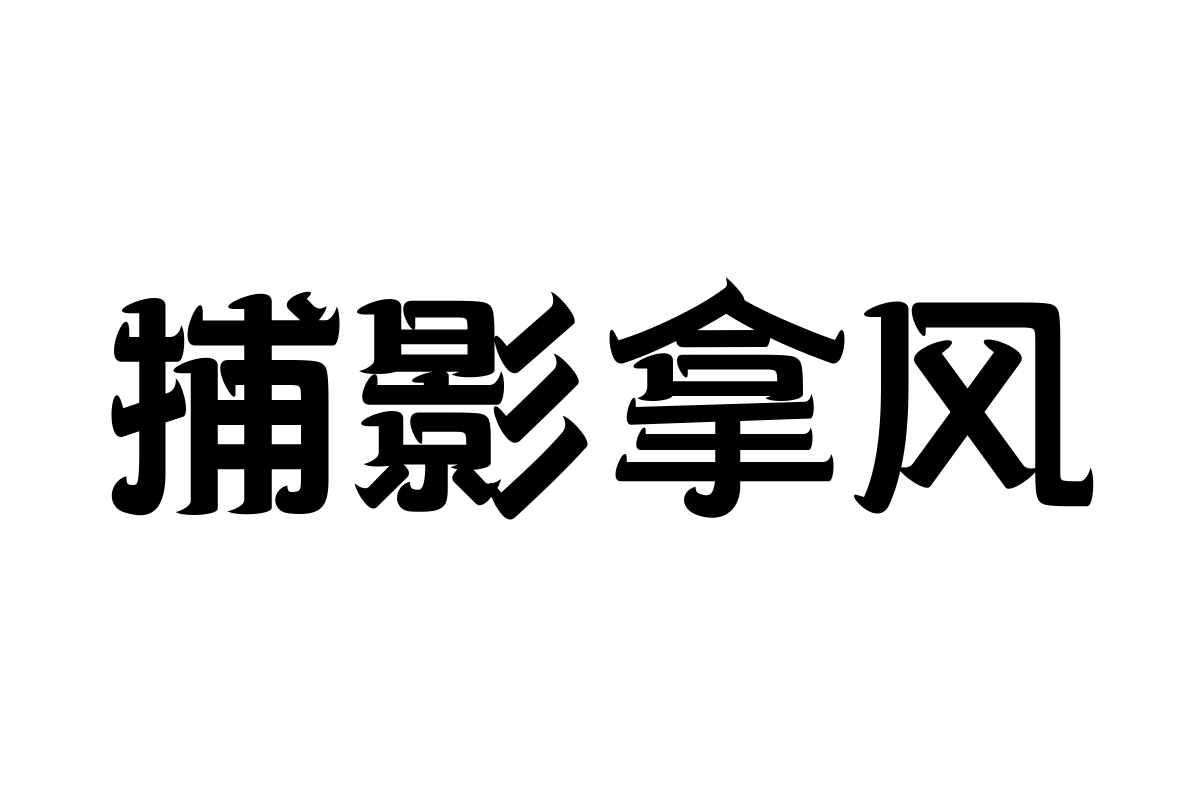
三极牛牛体是一种非常粗的字体,适用于需要强调和突出显示的场合。它的设计灵感来源于传统的中国书法,具有独特的韵味和艺术感。这种字体的特点是笔画粗壮有力,线条流畅自然,给人一种强烈的视觉冲击感。
三极牛牛体的字形结构紧凑而富有弹性,每个笔画都经过精心设计和调整,以确保整体的美观性和可读性。这种字体适用于各种类型的文本,包括标题、正文、广告等,能够有效地传达出强烈的视觉效果和情感表达。
总的来说,三极牛牛体是一种非常独特且实用的字体,适合用于需要强烈视觉冲击力的场合。